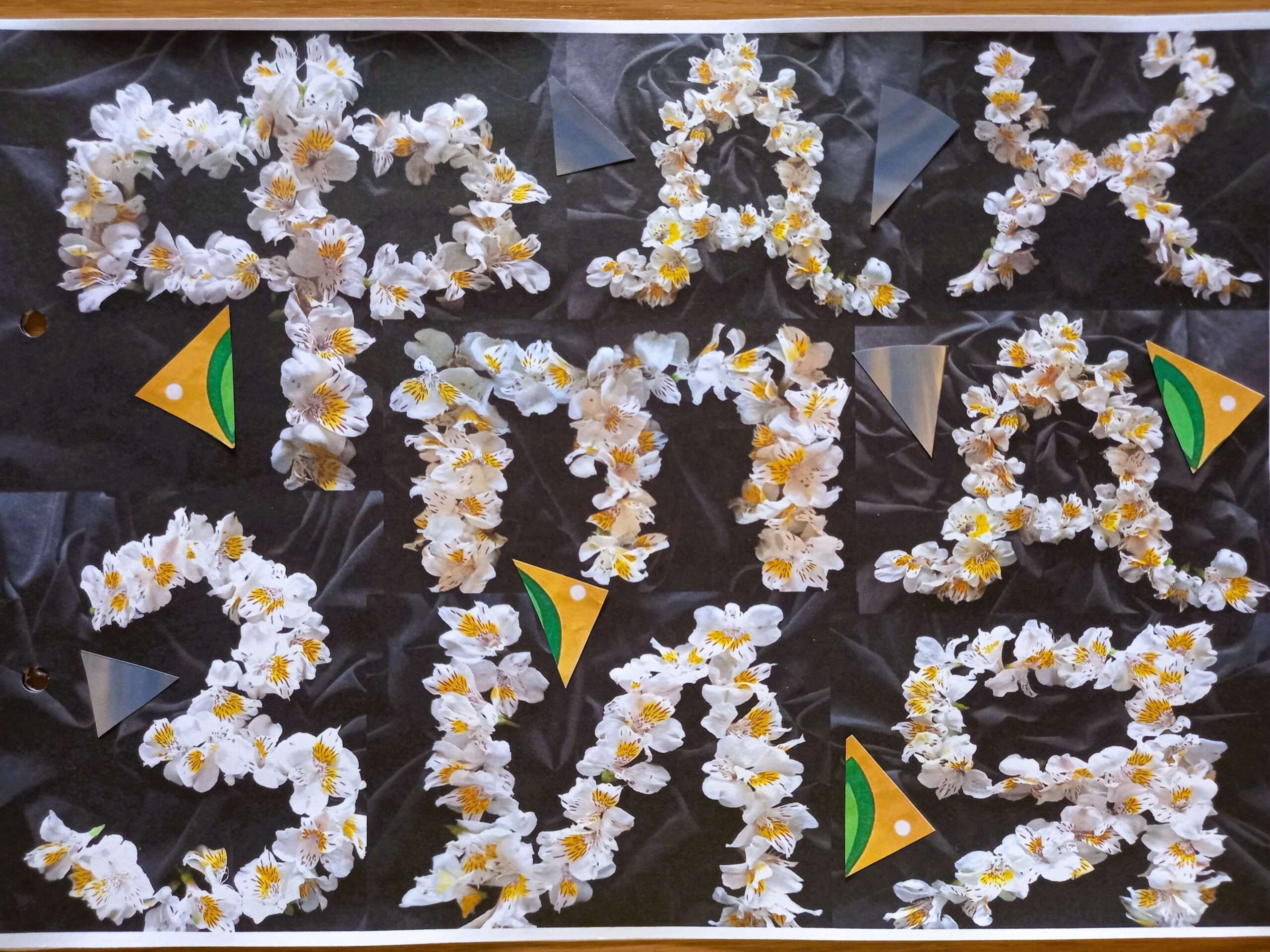
Фантазия. Шрифт Цветочный.
Буквы выполнены из живых бутонов цветов. Как это завлекательно и привлекательно и душисто! Собрала из цветочков и сфотографировала весь русский алфавит и цифры.